気鋭のデザイナーたちが表現する いま注目の作字アイデア104 偏愛文字図鑑
インプレスグループでデザイン分野のメディア事業を手がけるエムディエヌコーポレーションは、MdN編集部編集による、文字を愛するすべての人に捧げる気鋭のクリエイター25名が手がけた作字アイデア本「気鋭のデザイナーたちが表現する いま注目の作字アイデア104 偏愛文字図鑑」を発売した。
作字は「文字を作る」ことを指す。
作字のイメージは『趣味の範囲』『個人で楽しむ』という印象があるが、実際にはデザインの現場で多用されている。
用途はタイトルや見出し、ロゴ&シンボル、利用範囲も雑誌やポスター、広告といった紙媒体から、ミュージックビデオや映画、Webなどの映像系まで多岐にわたる。
文字単体(作字やタイポグラフィ、ロゴ)にも関心が高く、そのなかでも作字は非常に注目されている。
作字は「造形的な美しさ」と「可読性」を兼ね備えたもの。
言葉がもつイメージを体現化しつつ、作りたいデザインに落とし込まないといけない。
「気鋭のデザイナーたちが表現する いま注目の作字アイデア104 偏愛文字図鑑」では作字に欠かせないアイデアの出し方を作品とともに掲載。
「完成までのステップ」「推しポイント」「アレンジメント」のいずれかで解説している。
作り方ではなく「どのようなアイデアから作字されているか」を知ることができるのが特徴となる。
デザインテーマにあった印象的な文字を作りたい人、ロゴやシンボルマークへ発展させたい人、基本書体で工夫したい人、文字アイデアを参考にしたい人、無類の文字好き&作字好き&作字文化LOVEな人に手にとってもらいたい一冊となる。
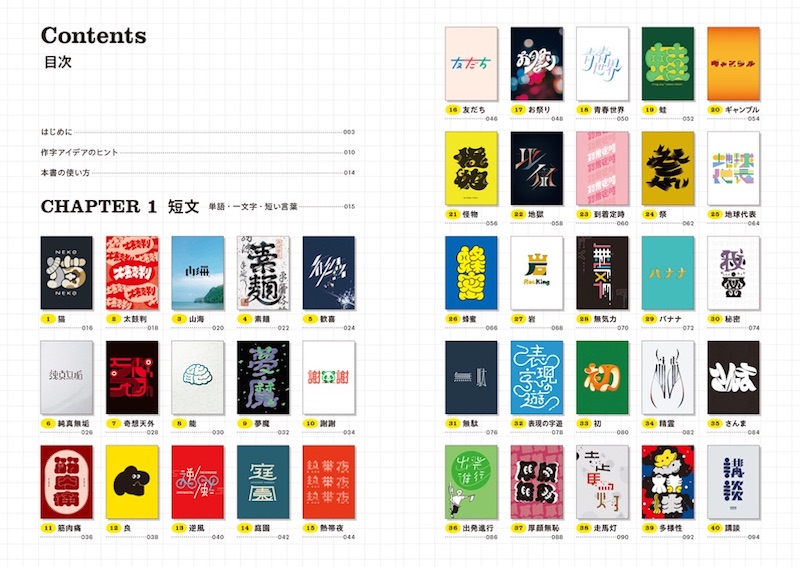
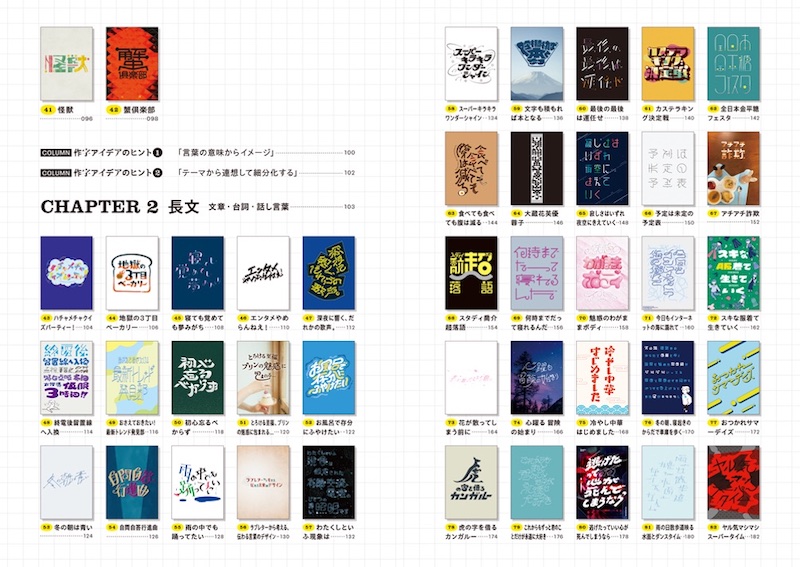
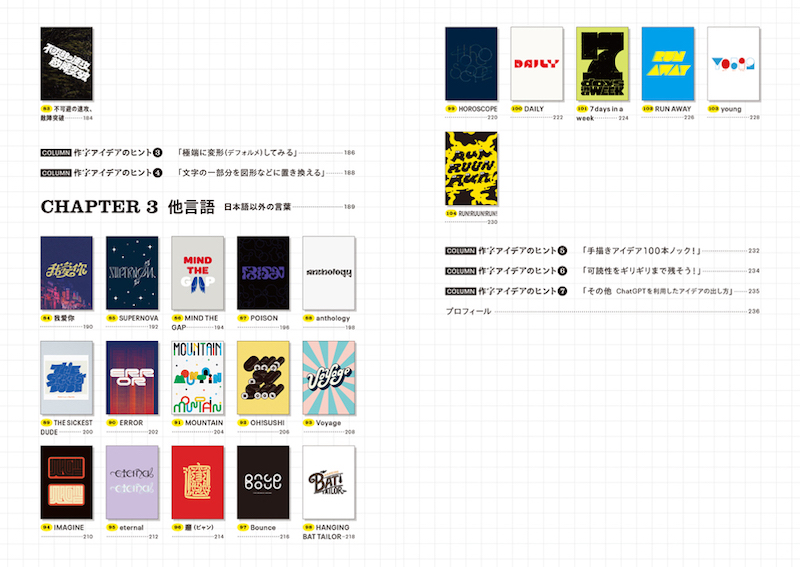
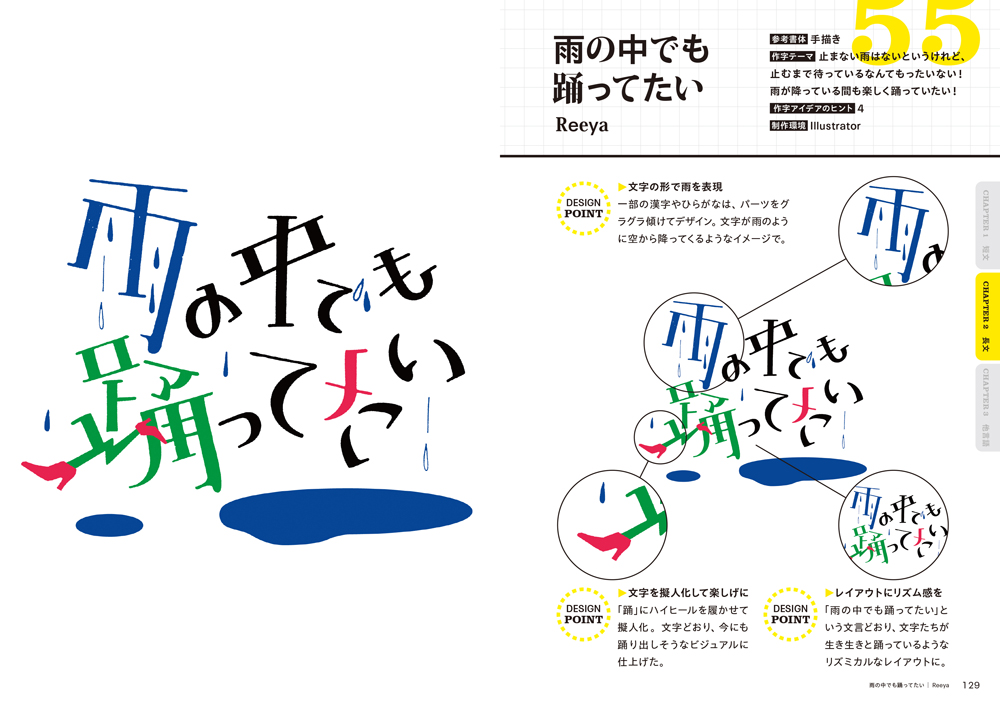
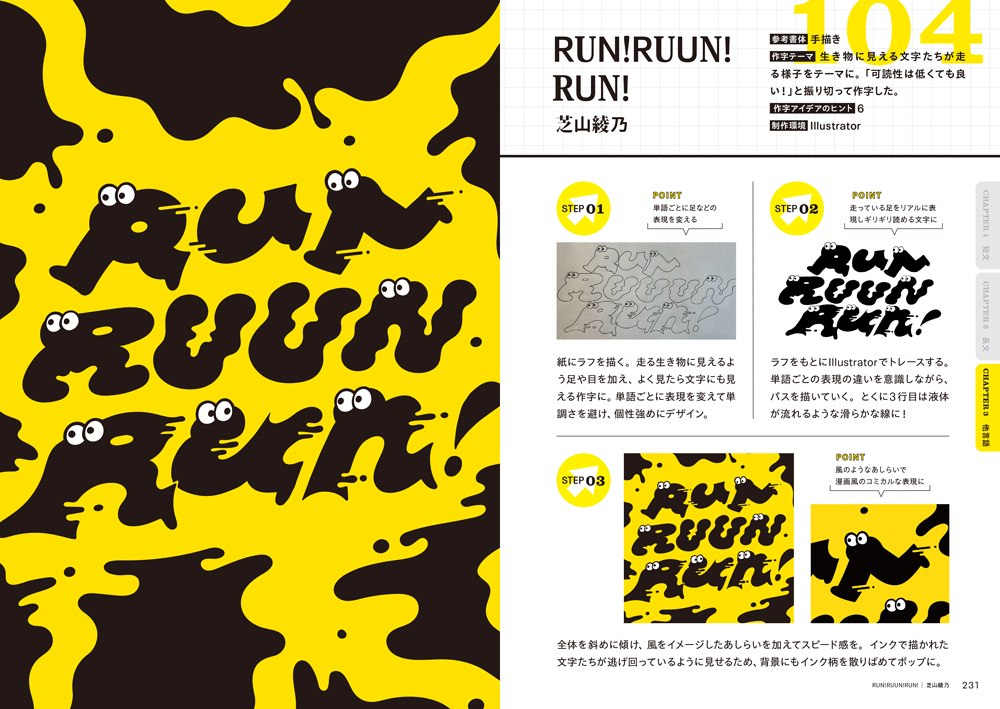
「気鋭のデザイナーたちが表現する いま注目の作字アイデア104 偏愛文字図鑑」の魅力
・基本書体で魅力的な文字デザインが作れる
・人気作字クリエイターの作字を一冊で網羅
・文字デザインアイデアの指南書